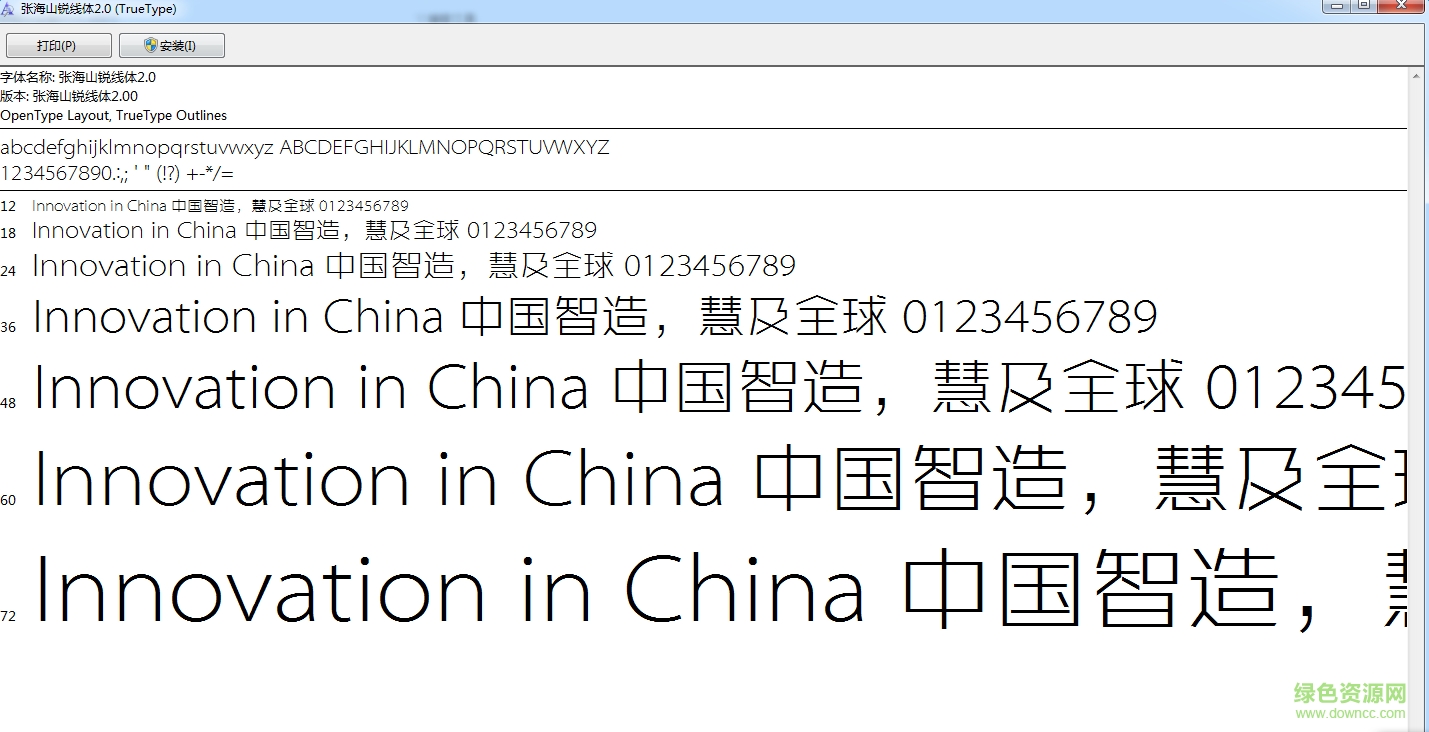
字體張海山銳線體2.0是一款纖細優(yōu)雅的簡體中文字體,該字體結(jié)構(gòu)嚴(yán)謹(jǐn),布白均勻,筆畫構(gòu)思精巧,排版效果出色,喜歡這款字體的朋友快來綠色資源網(wǎng)下載吧!
張海山銳線體2.0是一款實用性與欣賞性兼?zhèn)涞闹形淖煮w,字形美觀而不落俗套,看上去十分雅致,適用于大段文字排版中!